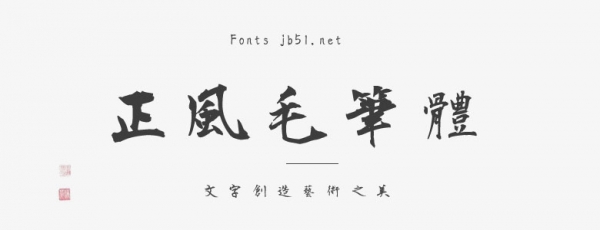
正風毛筆體(正風毛筆 MasaFont)是中國臺灣的設(shè)計師Max基于衡山毛筆行書進行字符增補的一款毛筆字體。衡山毛筆行書字體是來自于日本書法家青柳衡山,文字加符號數(shù)共7,582字,經(jīng)過Max的補充文字加符號數(shù)共23,699字。繁體字比較全,簡體字型有部分缺字現(xiàn)象。
相較于正風毛筆字體的師兄莫大毛筆體,正風在個性上就隨性很多,也造成有部份的一些字很粗,而有些字極細。原作者的“木”、“米”、“禾”系列常常會少一撇,是正常的,第一次看到會覺得有點怪,但是看久就會習慣了。
由于是正風毛筆字體并非原作者的親自手寫,而是使用人工智能的方式在學習原有字形的基礎(chǔ)上進行的增補。新加入的字在風格上,雖然力求一致,但是難免會與原作者會有一些不同。有很多很多字補的“超級丑”的,
正風毛筆字體包含了5個字重。原本的衡山毛筆行書字體放在Regular字重里,通過程序自動產(chǎn)生ExtraLight、Light、Medium、Bold等新的字重。Light字重是把原本的衡山毛筆行書微微調(diào)細一點點。在ExtraLight的字重裡,可能會因為筆劃太細造成某些筆畫消失。在Medium和Bold的字重里,可能會因為筆劃太粗造成某些筆畫重疊難以識別,有粗體字的需求,可以先嘗試使用Bold字重看看,如果發(fā)現(xiàn)效果不如預(yù)期,再改用Medium字重。不能確定自動產(chǎn)生出來的字重里每一個都是完整的字,畢竟程序誤判是常有的事情,所以不是在Regular字重里的筆劃可能會消失。